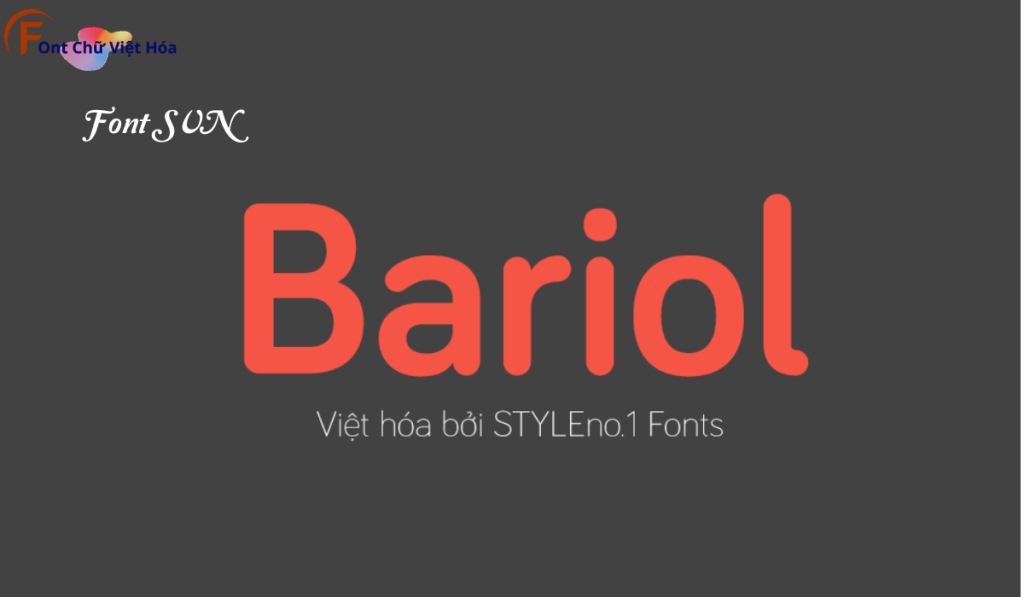
Font SVN Bariol Việt Hóa
Phân loại: Đẹp, mượt
Độ dày: Mỏng, Thường, Đậm, Đậm Đậm
Font SVN Bariol Việt Hóa là một font chữ không chân hiện đại, thuộc bộ font SVN. Được thiết kế với mục tiêu mang lại sự tinh tế và thanh lịch, font này phù hợp cho các dự án thiết kế như website, tài liệu, và bao bì sản phẩm. Với các nét chữ rõ ràng và độ dày đa dạng, Font SVN Bariol Việt Hóa không chỉ dễ đọc mà còn tạo cảm giác chuyên nghiệp và thân thiện. Việc Việt hóa font giúp người dùng dễ dàng sử dụng trong các thiết kế tiếng Việt, mang lại sự tiện lợi và thẩm mỹ cao.